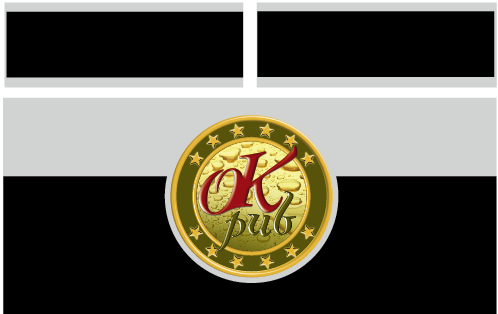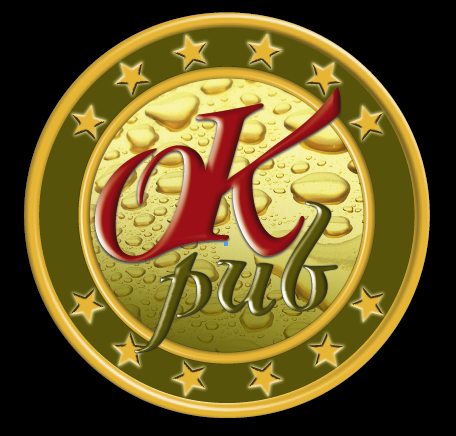
Welche Schriftart passt zu diesem Logo?
welche passende Schriftart könnte ich zu diesem Logo verwenden?
Es sollen große Fenster beschriftet werden. Die Schriftgröße schätze ich auf etwa 800pt ein.
Schön wäre es eine Schriftart zu haben, die ich ebenfalls für sämtliche Drucksachen verwenden könnte.
Hilfreich wärs wahrscheinlich, das Pub zu charakterisieren, dem du das vorgelegte Logo anheften willst und dazu zu schreiben, welche Art Drucksachen alles zu gestalten sind. Die verwendete Script taugt halt nicht für Fließtext und alles, was man in 9pt-Kolumnen gut lesen kann, wirkt im Regelfall in 800pt als Fensterbeschriftung doch ziemlich grobschlächtig. Da kommen dann eigentlich nur noch Schriften in Frage, die gut mit verschiedenen optischen Gewichten ausgebaut sind.
Ja und grundsätzlich: Hat denn der Entwurf wirklich Logo-Eignung? Ich mein, mit all den hübschen PS-Effekten, die halt in jeder Graustufenwiedergabe mit vielleicht 2cm Grafikgröße ziemlich kontraproduktiv sind. Von den Ergebnissen einer Fax-Übermittlung gar zu schweigen ...
Ja, das Logo ist für Drucksachen ungeeignet. Für die Drucksachen gibt es eine "einfache" Variante, zweifarbig (Pantone 484 und 581) und ohne Schatten sowie eine schwarz-weiße.
Es werden Visitenkarten, Briefbogen, Flyer und Plakate gedruckt.
Das abgebildete Logo wird auf zwei großen Fenstern in jeweils 1,20cm Durchmesser, auf schwarzem Hintergrund platziert (schwarze, matte Folie).
Da wünscht der Kunde auch etwas üppigeres mit Bild und Schatten.
Ebenfalls werden sämtliche Tische in dieser Form vollflächig beklebt (ca. 60x60cm). Aus Alt mach Neu :?
Zum Pub… ca 100m/2. Wände, Säulen wurden bereits abwechselnd in grün und rot ( wie o.g. Farben) gestrichen. Fußboden und Bar in Holz. Keine Blumen oder andere Dekoration außer Biergläser und TV . Hauptmotiv–Logo.
Besitzer: jung, modern und mit wenig Kapital :( :neenee:
Ungefähr so
finde ich gut! P22 sehr gut sogar.
Ähnliches habe ich ausprobiert aber diese Schriftart ist noch besser.